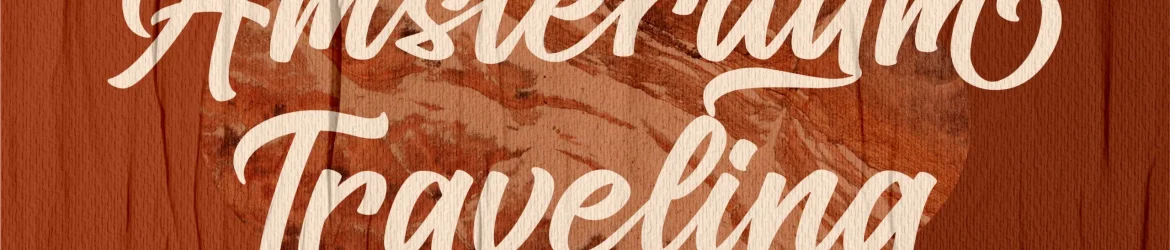
A fonte ‘Amsterdam Traveling Font’ é uma elegante escolha para qualquer projeto que exigir um toque sofisticado e personalizado. Especialmente projetada para ambientes como embalagens de produto, revistas, selos e cartões de visita, ela traz uma sensação de luxo premium a cada obra final. Esta fonte é perfeita para criar mensagens poderosas em mugs, adesivos e até mesmo em painéis publicitários. Com sua tipografia fluida e elegante, esta fonte é adequada para criações como nome cards, cartões de visita e materiais promocionais. Sua facilidade na manuseio também a torna uma opção ideal para designers digitais que buscam criar trabalhos profissionais em um curto período de tempo. Com o ‘Amsterdam Traveling Font’, você pode capturar o espírito da viagem, oferecendo aos seus clientes e consumidores uma experiência visual atraente. E embora seja projetada principalmente para aplicativos na linha do design gráfico, ela é perfeita para qualquer projeto que exija um toque singular de sofisticação. Essa fonte pode ser usada em tudo desde selos até capas de livros e maquetes de revistas. Ela atende a uma variedade de necessidades criativas e empresariais, tornando-se uma verdadeira aliada para qualquer designer ou marca que está buscando um toque sofisticado e elegante em seus trabalhos.